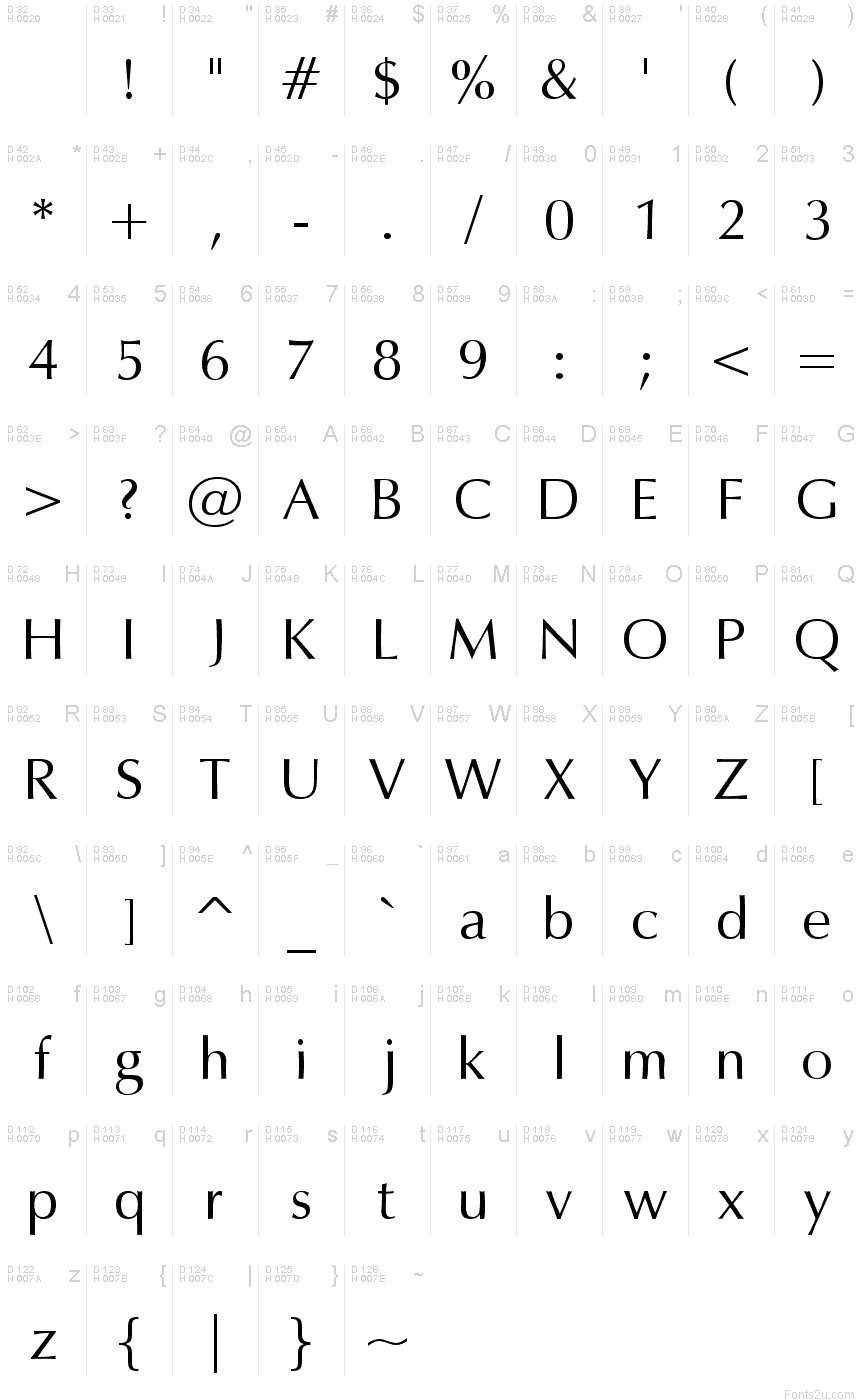
Vera Humana 95
Vera Humana 95 od BX Fonts je bezplatné humanistické bezpatkové písmo z roku 1997, jehož písmena působí spíše nenápadně klasicky než neutrálně. Styl vychází z kaligrafického rytmu – ostré diagonály, otevřené zaoblené tvary a jemný kontrast dodávají písmu literární, pozdně moderní nádech.
Hodí se pro redakční identity, obálky knih, muzejní materiály, kulturní plakáty a titulky, kde hledáte bezpatkové písmo s jistou mírou vřelosti a vyváženosti. Jako bezplatný font dává smysl i pro obálkové texty, úvody sekcí a krátké brandingové momenty, protože písmena nesou dostatek pohybu, aby působila promyšleně, aniž by se stala příliš zdobnými.